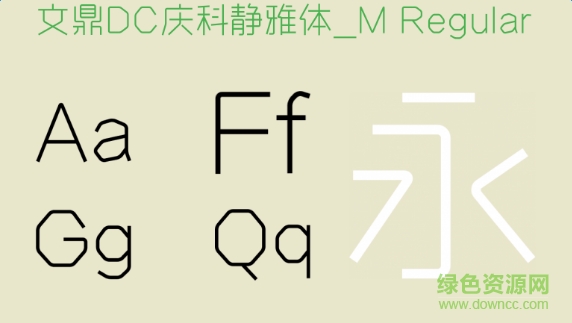
文鼎DC慶科靜雅體是文鼎字庫(kù)中的一款常用的廣告字體,這款字體轉(zhuǎn)角設(shè)計(jì)十分精巧,線條松緊適中,字形柔美而不失剛毅,喜歡這款字體的小伙伴快來(lái)綠色資源網(wǎng)下載吧!
文鼎DC慶科靜雅體,是一款黑體與綜藝體的結(jié)合體,字體筆畫(huà)美觀大方,字型特點(diǎn)是簡(jiǎn)、直、連,具有較大范圍的應(yīng)用空間。適用于高端品牌廣告與平面設(shè)計(jì)。